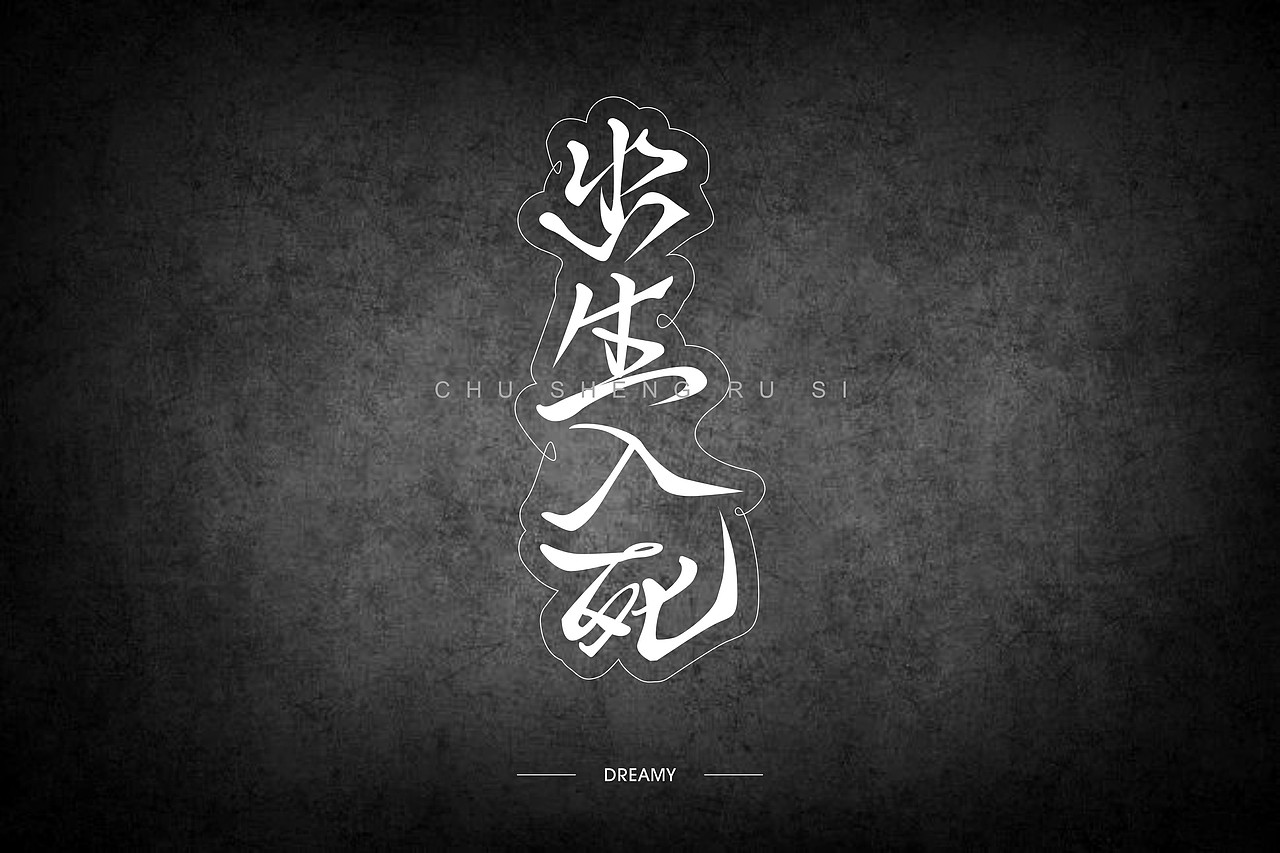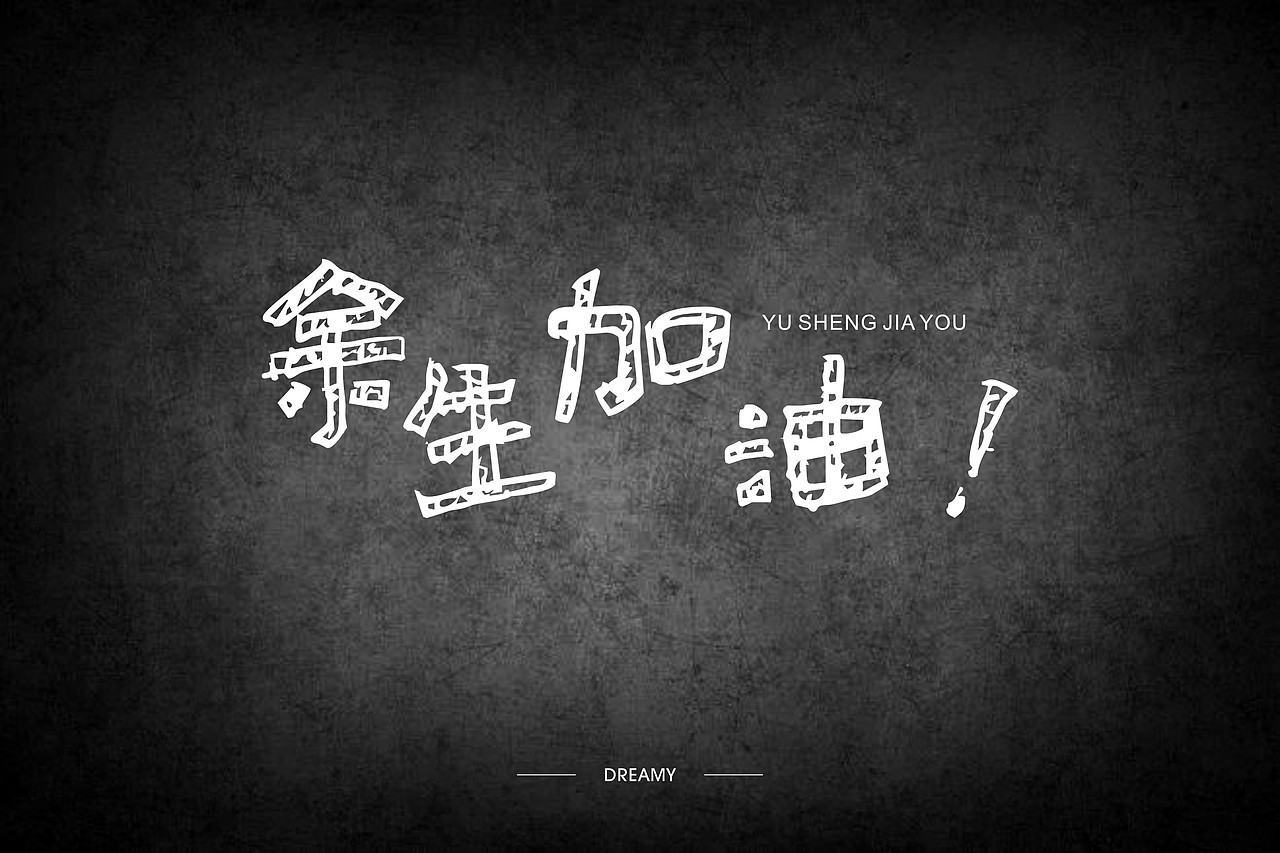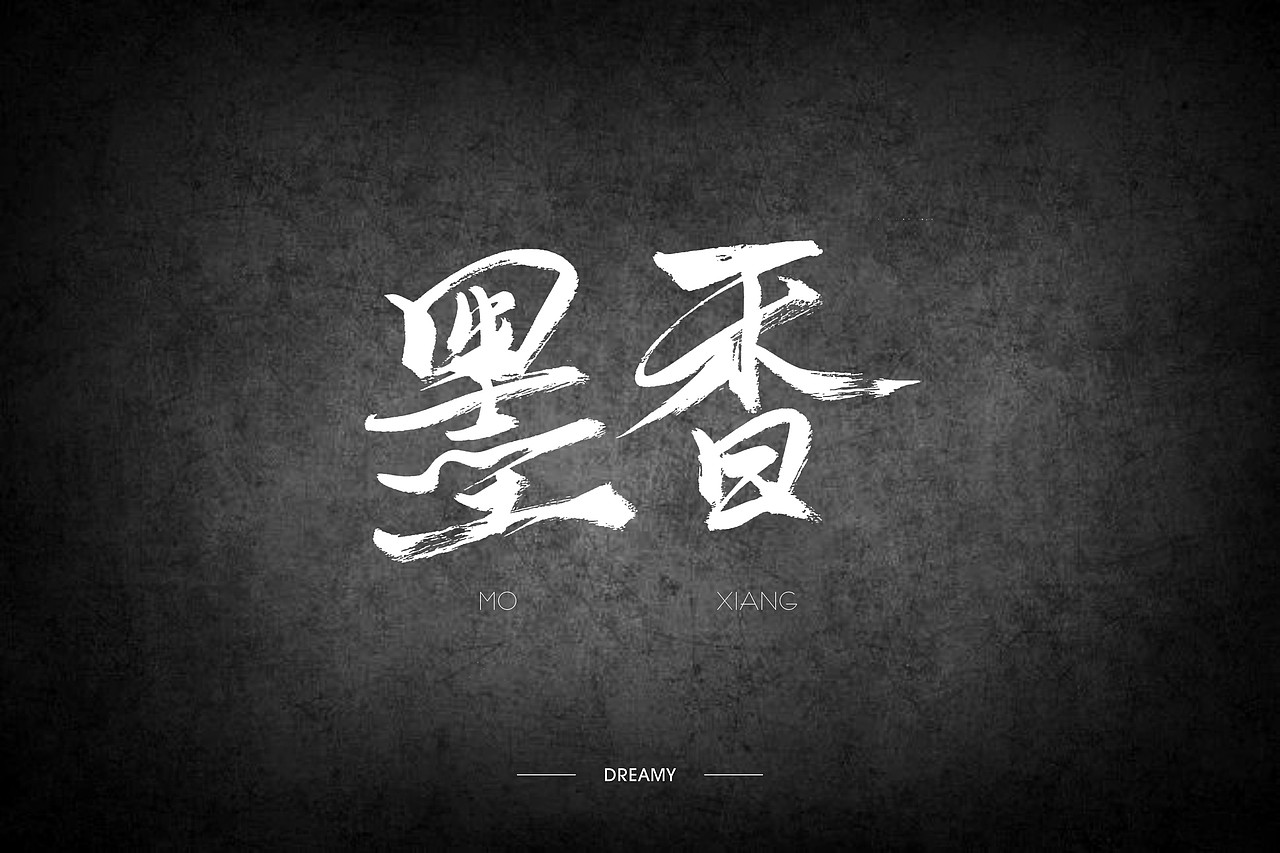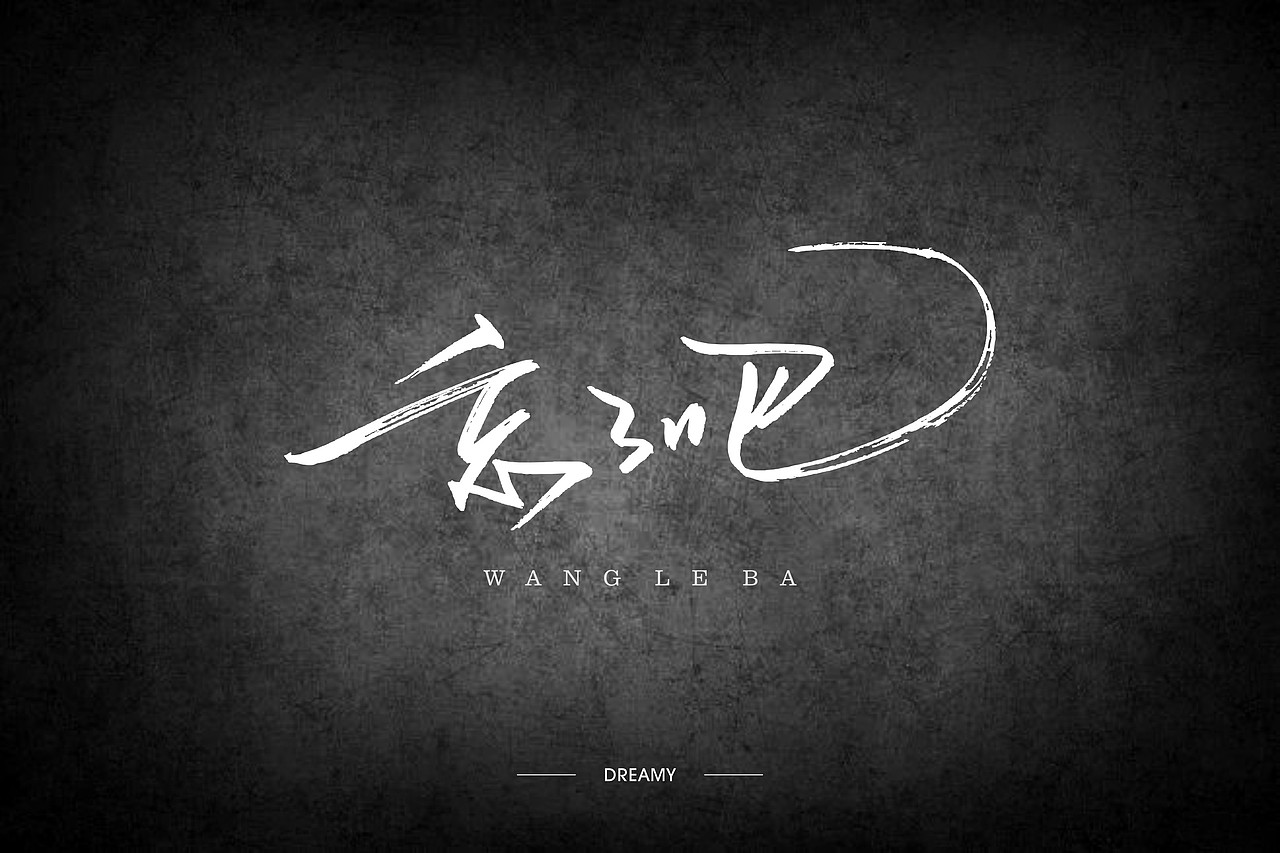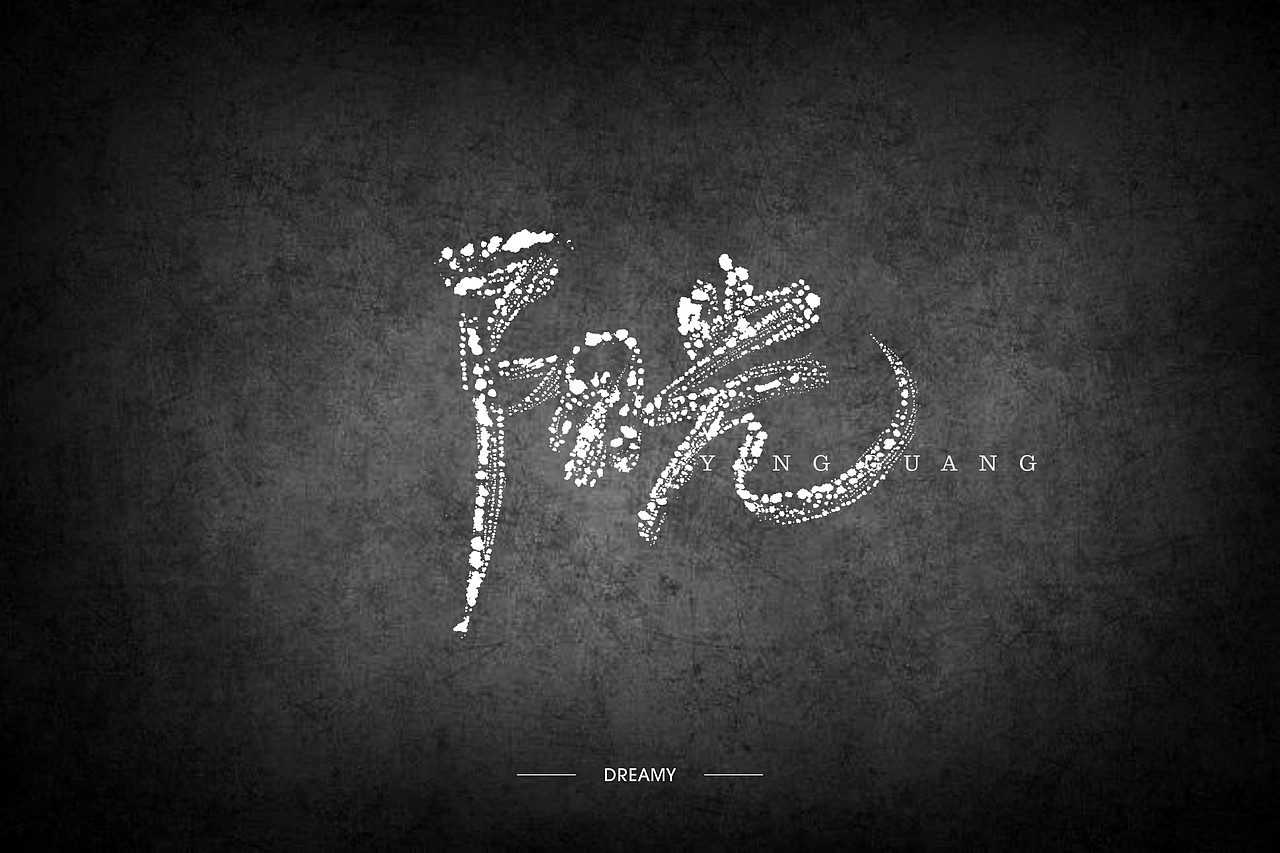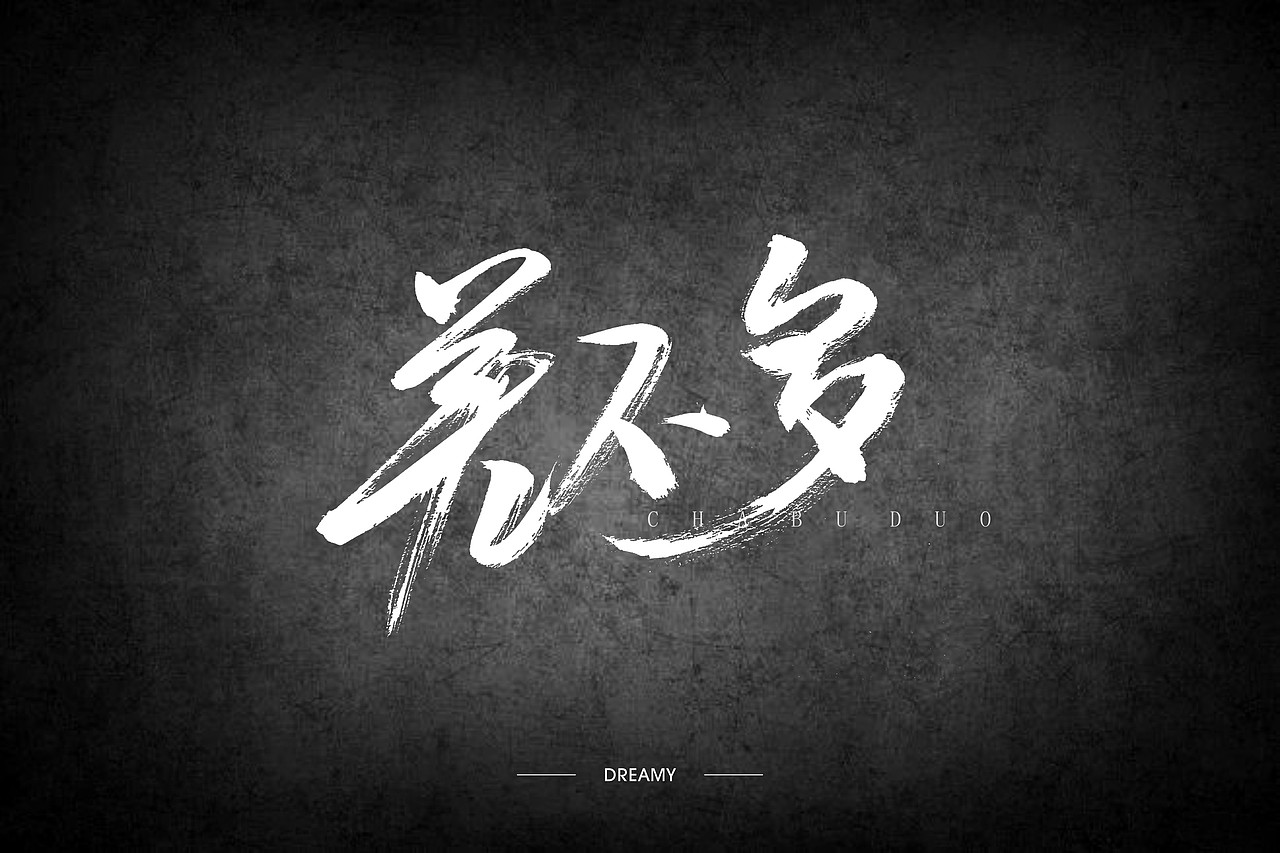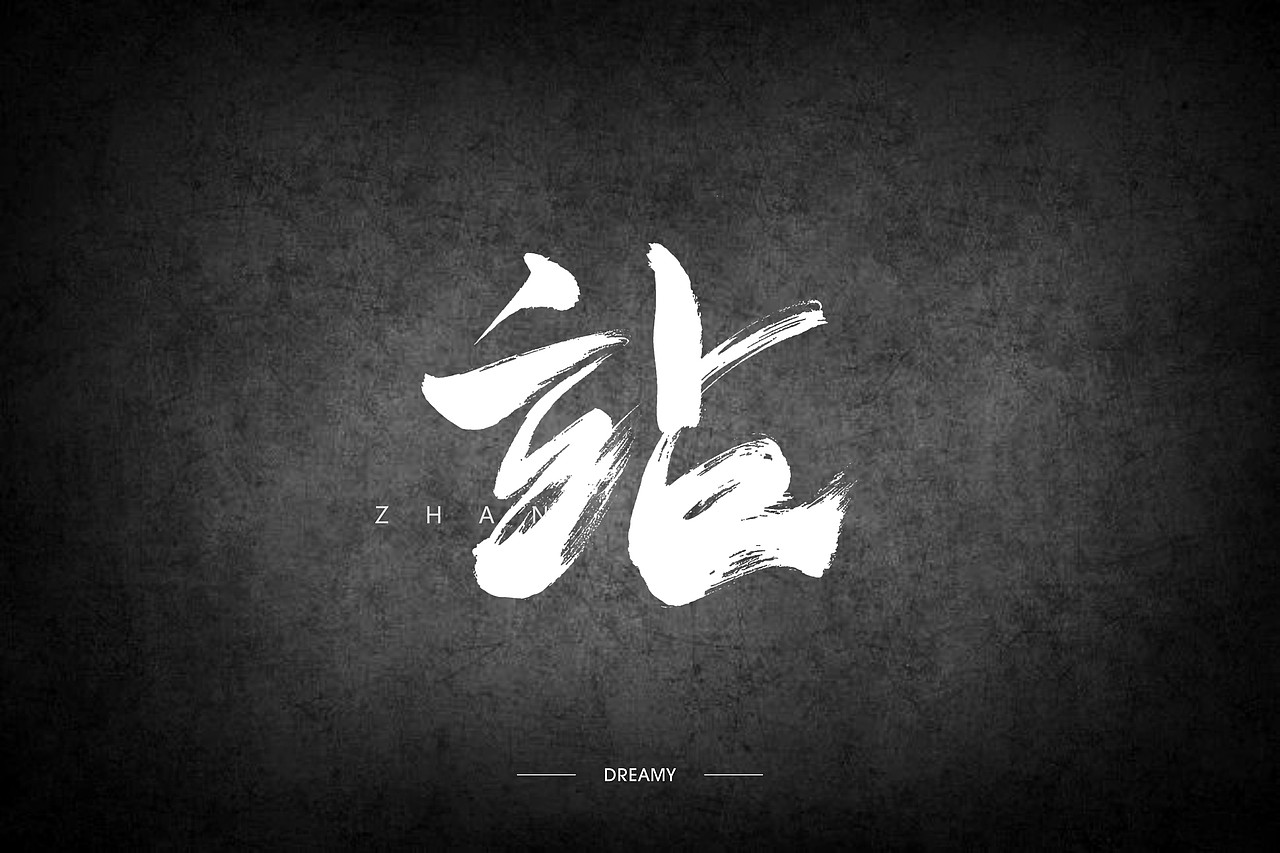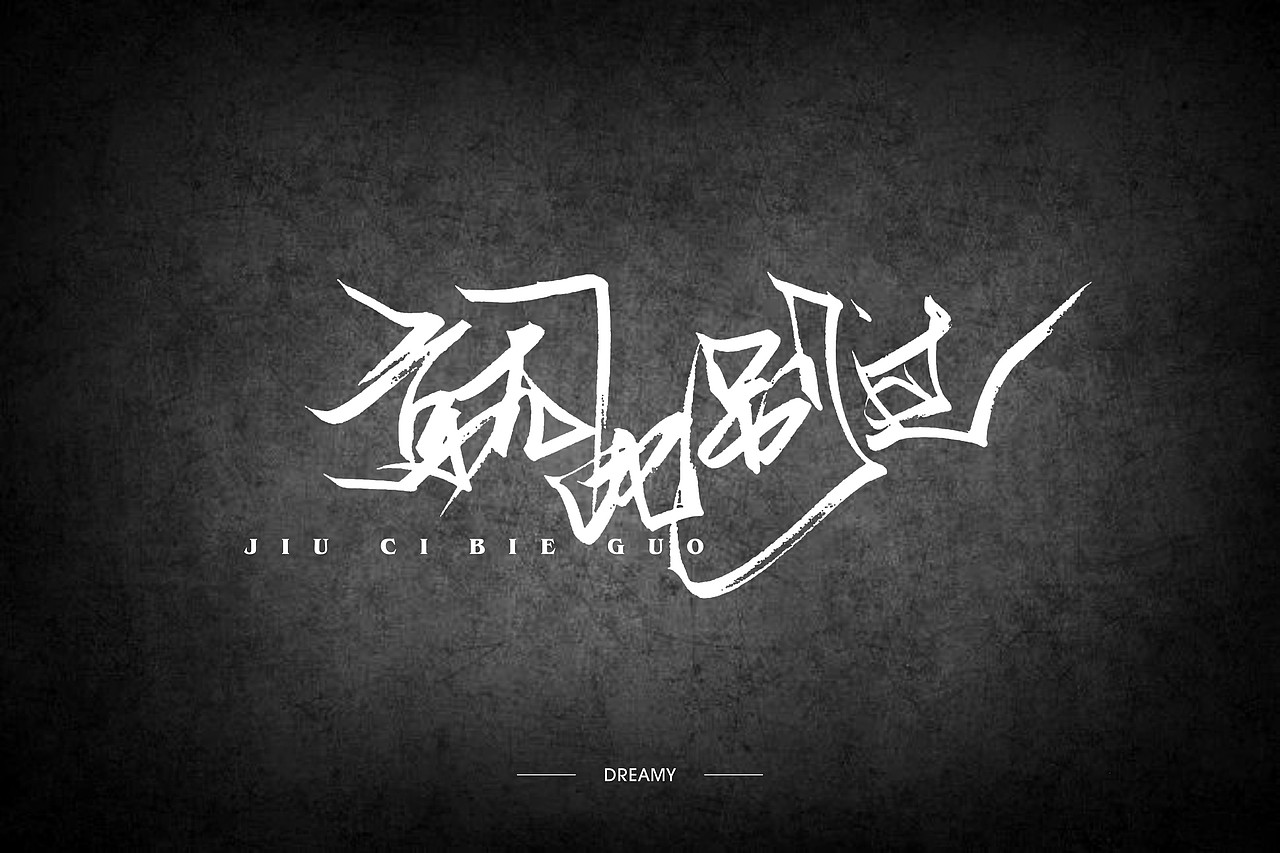
二零一七的七月-还是结束了
敬一杯烈酒
至昨日夕阳,
燃半支香烟
愿明日不枉。
羡一生如此,曲折波澜,有人陪。
可悉数昨日过往,但谁都无法计算余生,或长或短,愿余生加油。
被悲催的现实阻挠着,每日生活于不想也不愿中,够了。
谁都有外人不曾理解的故事,心酸或幸福。经历就好。
我喜欢闻着墨香,可能疏于结构,疏于笔法,但不疏于情感。
我愿乘风破浪,踏遍黄沙海洋。
绝不迎合,那又怎样。
忘了吧,昨日喜悲。
阳光太刺眼,还是黑夜安静点。
旧人若离别,忘个干净吧。
泪,可喜可悲。释放而已。
烟可解忧,亦可消愁。好东西。
差不多先生,差不多的话,差不多的人,差不多的事。
就一点,也很多。
站,占,
何必呢,让自己那么可怜。
知己好友,胜过千万,
就此别过,七月。